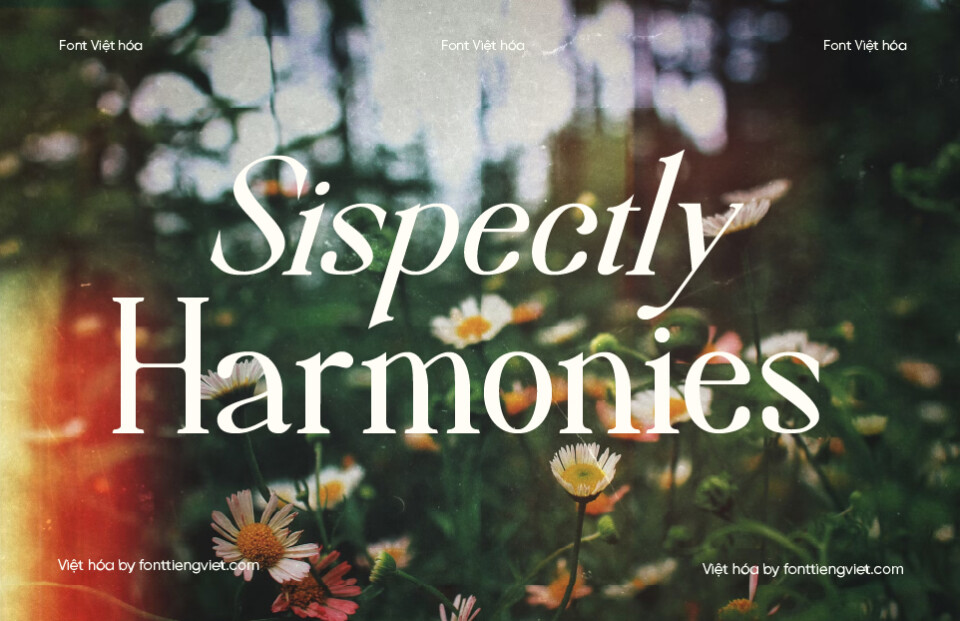
Font Việt hóa 1FTV VIP Sispectly Harmonies
Font Việt hóa 1FTV VIP Sispectly Harmonies – Đỉnh Cao Sáng Tạo Cho Thiết Kế Việt
Giới thiệu về Font Việt hóa 1FTV VIP Sispectly Harmonies
Trong thế giới thiết kế đồ họa hiện đại, việc lựa chọn một bộ Font Miễn Phí chất lượng luôn là ưu tiên hàng đầu của các designer. Đặc biệt, bộ Font Việt hóa 1FTV VIP Sispectly Harmonies đã nhanh chóng trở thành một hiện tượng trong cộng đồng sáng tạo nhờ sự kết hợp hoàn hảo giữa nét cổ điển và hơi thở đương đại. Đây không chỉ đơn thuần là một công cụ gõ văn bản, mà còn là linh hồn giúp các ấn phẩm truyền thông trở nên sống động và có chiều sâu hơn. Việc sở hữu một bộ phông chữ được tối ưu hóa đầy đủ dấu tiếng Việt giúp người dùng tránh được các lỗi hiển thị khó chịu, đồng thời đảm bảo tính thẩm mỹ cao nhất cho mọi dự án từ học đường đến chuyên nghiệp.
Đặc điểm nổi bật của bộ Font Việt hóa 1FTV VIP Sispectly Harmonies
Nét chữ thanh thoát và đầy tính nghệ thuật
Điểm thu hút nhất của Font Việt hóa 1FTV VIP Sispectly Harmonies chính là cấu trúc đường nét vô cùng tinh tế. Các ký tự được chăm chút tỉ mỉ với những đường cong mềm mại, tạo cảm giác uyển chuyển như những nốt nhạc trong một bản hòa tấu. Sự cân bằng giữa độ dày và mảnh của các nét chữ giúp bộ font này có khả năng ứng dụng linh hoạt trên nhiều chất liệu khác nhau. Cho dù bạn đang thiết kế một tấm thiệp mời sang trọng hay một bìa sách nghệ thuật, Sispectly Harmonies luôn biết cách làm nổi bật nội dung mà không gây rối mắt cho người xem.
Khả năng tương thích và tính ứng dụng cao
Một trong những lý do khiến Font Việt hóa 1FTV VIP Sispectly Harmonies được yêu thích là nhờ sự tương thích tuyệt vời trên các phần mềm thiết kế phổ biến như Adobe Photoshop, Illustrator hay Canva. Đội ngũ kỹ thuật của 1FTV đã tiến hành Việt hóa kỹ lưỡng, đảm bảo các ký tự có dấu như “ă”, “â”, “ơ”, “ư” và các dấu thanh được đặt đúng vị trí, giữ nguyên tinh thần bản gốc của tác giả. Điều này cực kỳ quan trọng đối với các bạn học sinh, sinh viên khi làm báo cáo hoặc bài thuyết trình, giúp sản phẩm cuối cùng trông chuyên nghiệp và chỉn chu hơn bao giờ hết.
Kết luận về bộ phông chữ đặc sắc
Tổng kết lại, bộ Font Việt hóa 1FTV VIP Sispectly Harmonies là một sự lựa chọn không thể bỏ qua cho bất kỳ ai đang tìm kiếm sự đột phá trong phong cách trình bày. Với sự tỉ mỉ trong khâu Việt hóa và tính thẩm mỹ vượt trội, nó xứng đáng có mặt trong thư viện tài nguyên của bạn. Nếu bạn đang tìm kiếm thêm nhiều lựa chọn khác, hãy truy cập ngay Font Miễn Phí, Font Việt Hóa, Font Việt hóa 1FTV VIP Sispectly Harmonies để khám phá thế giới chữ viết đầy màu sắc và sáng tạo. Chúc các bạn có những tác phẩm thiết kế ưng ý và đầy ấn tượng với bộ phông chữ tuyệt vời này!